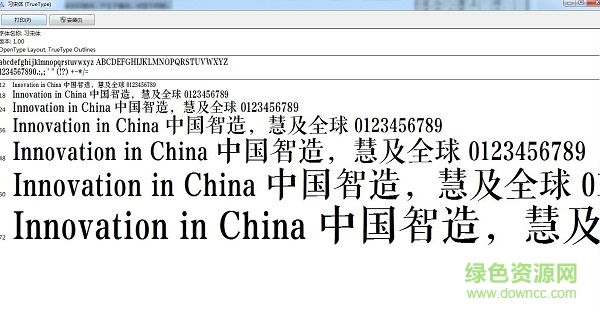
sgsxst是什么字體?sgsxst字體又叫習(xí)宋體,是一款美觀新穎的宋體字體,結(jié)構(gòu)簡潔,排印清晰,適用于網(wǎng)頁設(shè)計、書刊報紙等各個領(lǐng)域,有需要者快來本站免費(fèi)下載吧!
宋體是生而具來的印刷體,產(chǎn)生于雕版,成型于明朝。在宋體字出現(xiàn)之前,印本的字體都是手書的楷體。明初內(nèi)府刻本中的楷書字體還曾傳入朝鮮半島,成為其官方鑄造金屬活字的字體。